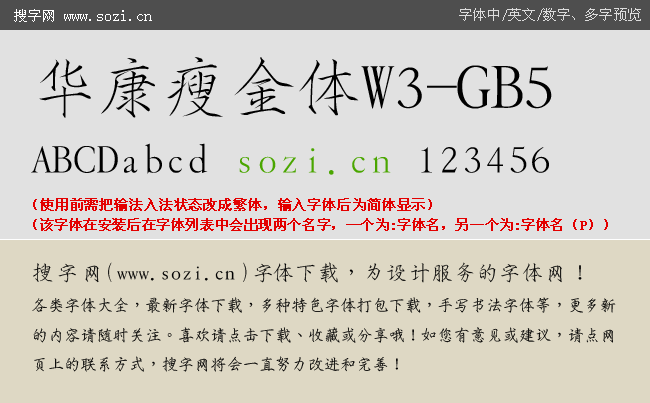
華康瘦金體簡W3-GB5
搜字網(wǎng)提供一款書法字體華康瘦金體簡W3-GB5字體下載,瘦金體為宋徽宗趙佶所創(chuàng),是書法史上的一項獨創(chuàng)。瘦金體運筆飄忽快捷,筆跡瘦勁,至瘦而不失其肉,轉(zhuǎn)折處可明顯見到藏鋒,露鋒等運轉(zhuǎn)提頓痕跡,是一種風格相當獨特的字體。適合字貼、招貼、書法畫冊設(shè)計應用。